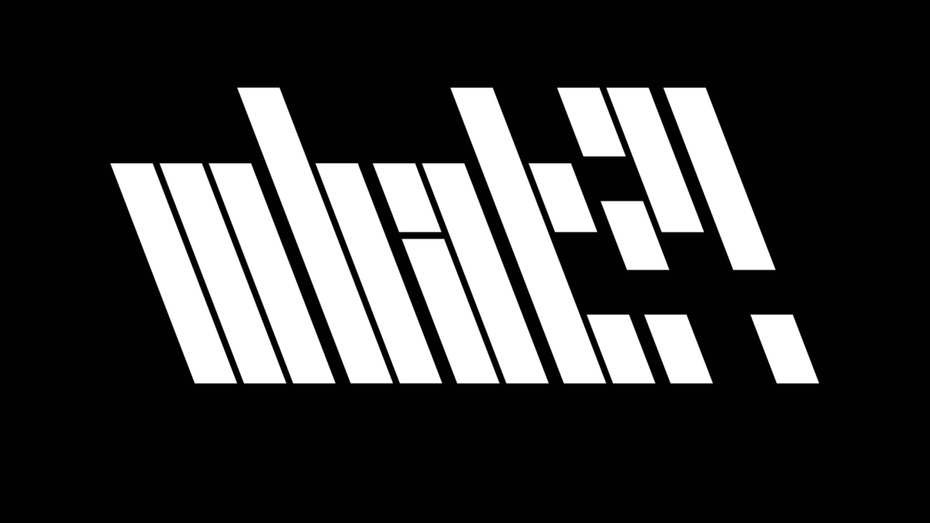
Warum eine Agentur eine Schriftart gebaut hat, die nur aus Backslashes besteht
Ein Design-Studio hat eine Schriftart erschaffen, die nur aus Backslashes besteht. Lesen kann das kaum jemand. Wozu ist sie also gut?
Bei diesem „What?“ lässt sich noch gerade so erkennen, was hier geschrieben ist (Grafik: Cotton Design/ Backslash).
Im normalen Alltag kommt vielen das Backslash (\) kaum in die Quere. Für Programmierer:innen ist das Zeichen dagegen essenziell. Ohne einen Backslash lässt sich kein Code schreiben. Als Schriftart taugt der Diagonalstrich auf jeden Fall nicht. Oder doch?
Das Gegenteil versucht die Agentur Cotton Design zu beweisen. Die Schriftart \Type besteht nur aus Backslashes und ist kaum lesbar. Besonders die Buchstaben mit vielen Details sind schwer zu erkennen. Für den Alltag ist sie also nicht zu verwenden. Dafür sieht sie ziemlich futuristisch aus. Zusätzlich gibt es immer weitere Varianten, die aus detaillierteren Backslashes bestehen und dadurch sogar lesbarer werden.
Die Schriftart ist jedoch nicht für die allgemeine Benutzung gedacht. Denn die Agentur hat \Type speziell für eine Organisation mit dem Namen Backslash im Rahmen des Rebranding entwickelt. Die Initiative ist Teil des technologieorientierten Campus der Cornell University in New York City und fördert kreative Projekte, die sich mit neuen Technologien auseinandersetzen. Auch der Name ist Teil der neuen Marke. Vorher hieß die Organisation \Art. „Die Umbenennung in ‚Backslash‘ verdeutlicht den Fokus auf das Überschreiten von Grenzen und die Nutzung von Technologie, um traditionelle Ansätze zu überwinden“, heißt es auf der Webseite der Agentur.
Ein komplettes Rebranding
Neben der neuen Schriftfamilie überarbeitete die Agentur auch das Logo von Backslash, das natürlich wie der Coding-Backslash gewinkelt ist. Auch eine neue Webseite und einen unendlichen Backslash-Mustergenerator erstellte die Agentur. Letzteres ist von Webmustern inspiriert und wird automatisiert von Code generiert.
Zu den Projekten von Backslash gehören Kunstprojekte, die mit neuen Technologien erstellt werden. So entstanden unter anderem Sprachmodelle auf Basis von GPT-2, die Texte von südchinesischen Aktivist:innen aufbewahren sollen. Ein weiteres Projekt ist eine Augmented-Reality-App für Mobiltelefone.